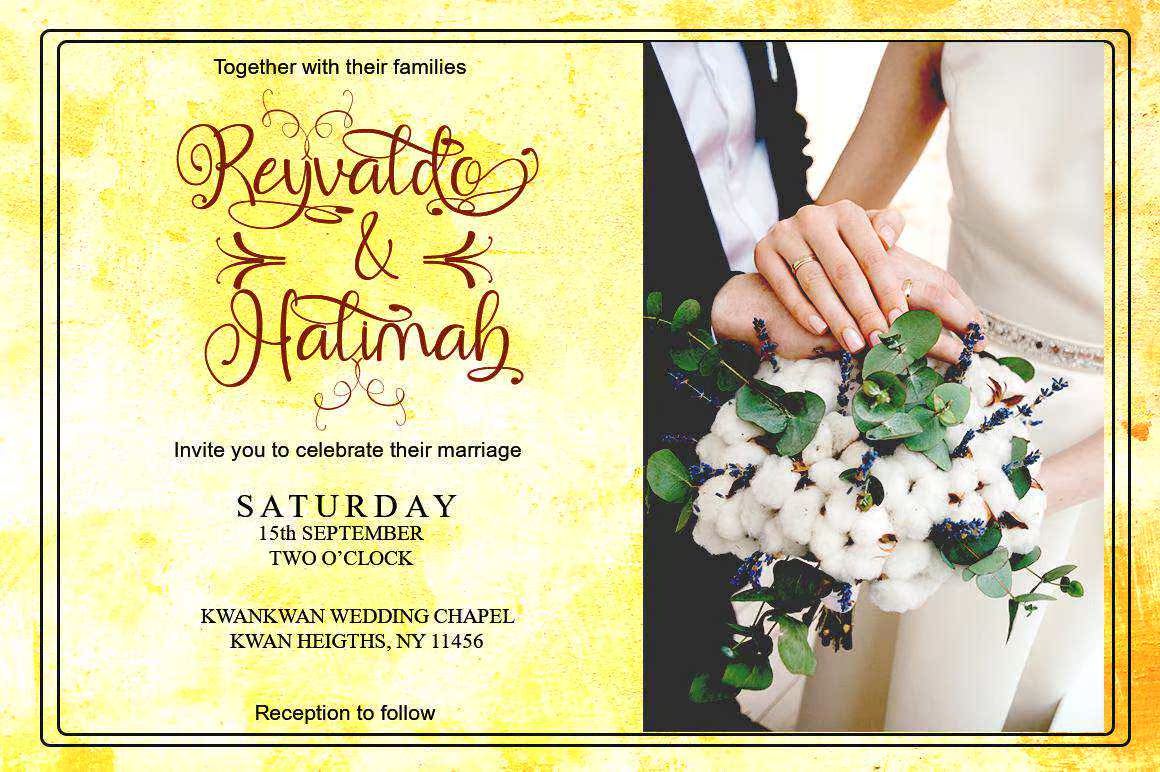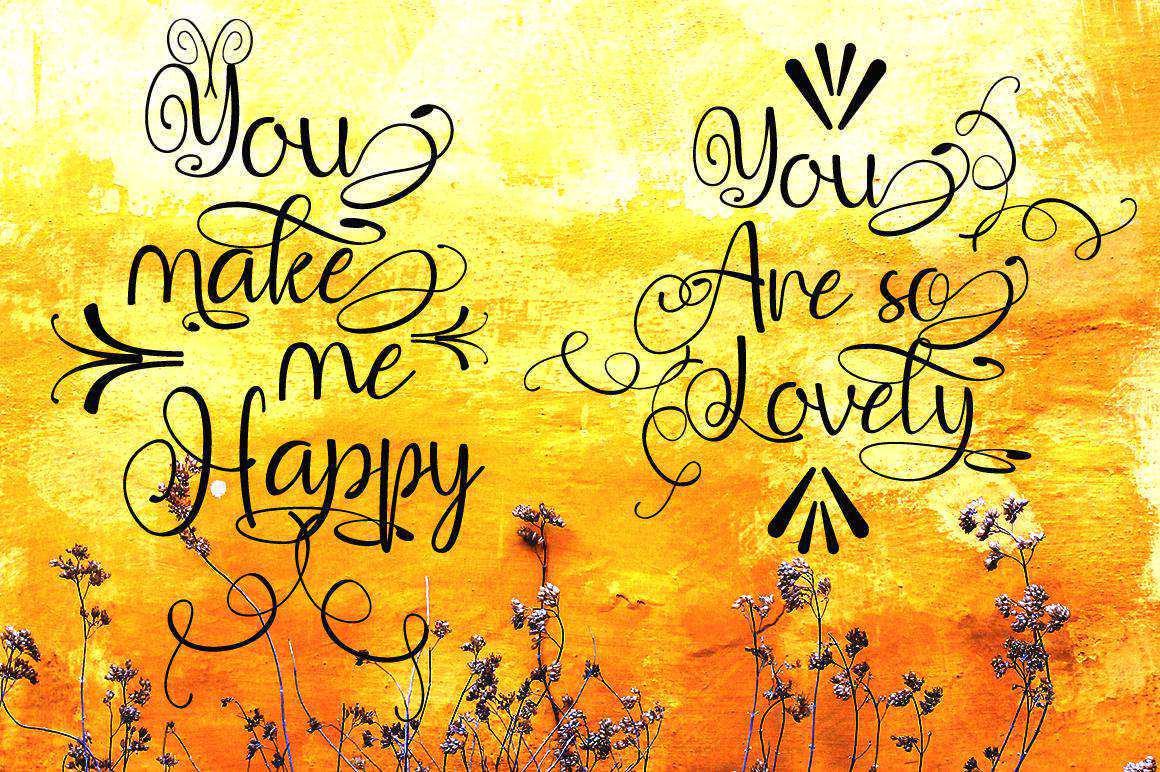
介绍。BehodakGaisa和书面、流畅、现代和经典、书法波浪形,这是为满足您下一个设计项目的需要而创建的。StillShine可用于各种用途。例如标题、签名、徽标、信函、婚礼宣传、信头、标牌、标签、时事通讯、海报、徽章等。介绍。BehodakGaisa和书面、流畅、现代和经典,书法是为满足您下一个设计项目的需要而创作的。StillShine可用于各种用途,如标题、签名、徽标、信函、婚礼宣传、信头、标牌、标签、通讯、海报、徽章等。